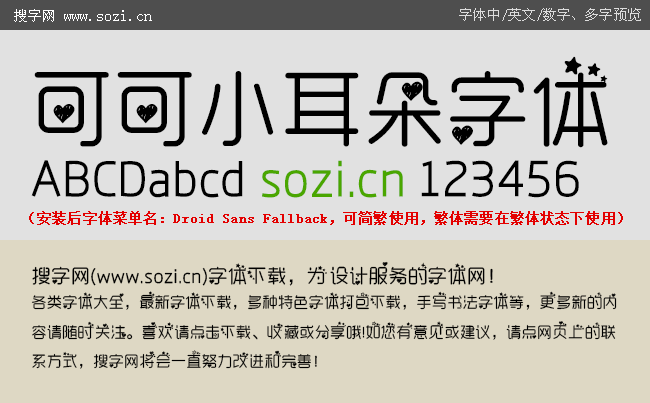
可可小耳朵字體
搜字網(wǎng)給大家提供一款很有趣的手機(jī)中文字體下載。字體名字叫可可小耳朵字體,這款手機(jī)字體是在造字工房悅黑體字體筆畫間插入了可愛的卡通圖案。趣味性實(shí)足,又保持了文字的識(shí)別度,特別適合喜歡手機(jī)字體個(gè)性一些的朋友在手機(jī)上安裝使用。